Подбираем шрифты с умом для создания привлекательных карточек товаров
Выбор подходящих шрифтов для карточек товаров имеет большое значение для их эффективности. Правильно подобранные шрифты создадут привлекательный дизайн и помогут привлечь внимание потенциальных покупателей. В этой статье мы расскажем вам, как выбрать идеальные шрифты для создания эффективных карточек товаров.
Используйте читаемые шрифты с хорошим отображением на любых устройствах. Они должны быть удобными для чтения и не вызывать напряжение глаз.
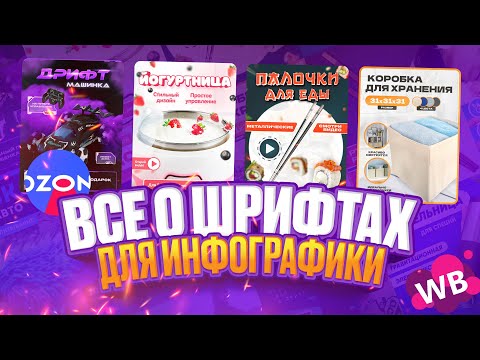
Учитывайте брендовую идентичность и стиль вашего магазина при выборе шрифтов. Они должны соответствовать общей атмосфере и визуальному образу вашей компании.
Не используйте слишком маленький размер шрифта, чтобы информация на карточке товара была легко читаема.
Избегайте использования слишком много разных шрифтов на одной карточке товара. Оптимально использовать два-три шрифта для создания гармоничного и сбалансированного дизайна.
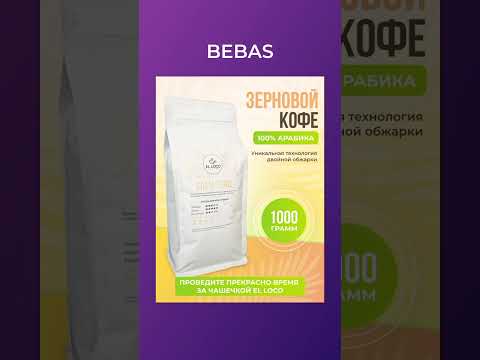
Шрифты для дизайна карточек товаров
Проверьте шрифты на совместимость с различными браузерами и устройствами. Они должны отображаться одинаково хорошо на всех платформах.
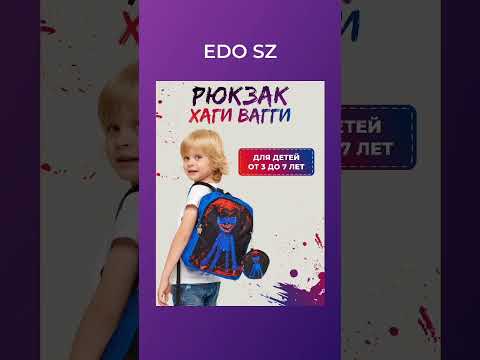
Шрифты для дизайна карточек товаров
Используйте шрифты, подходящие для вашей целевой аудитории. Например, для молодежных товаров можно выбрать более современные и стильные шрифты, а для товаров для пожилых людей - более удобные и читаемые.
Экспериментируйте с различными комбинациями шрифтов и их размерами. Иногда неожиданные сочетания создают самый запоминающийся дизайн.
Не забывайте учитывать контрастность шрифтов на фоне карточки товара. Они должны хорошо читаться и выделяться среди других элементов.
При создании карточек товаров для мобильных устройств выбирайте шрифты, которые хорошо смотрятся на небольших экранах и имеют достаточное расстояние между символами.
Не бойтесь экспериментировать с разными шрифтами до тех пор, пока не найдете идеальные для своих карточек товаров. Помните, что шрифт - это один из ключевых визуальных элементов, который может существенно повысить конверсию и привлекательность вашего магазина.